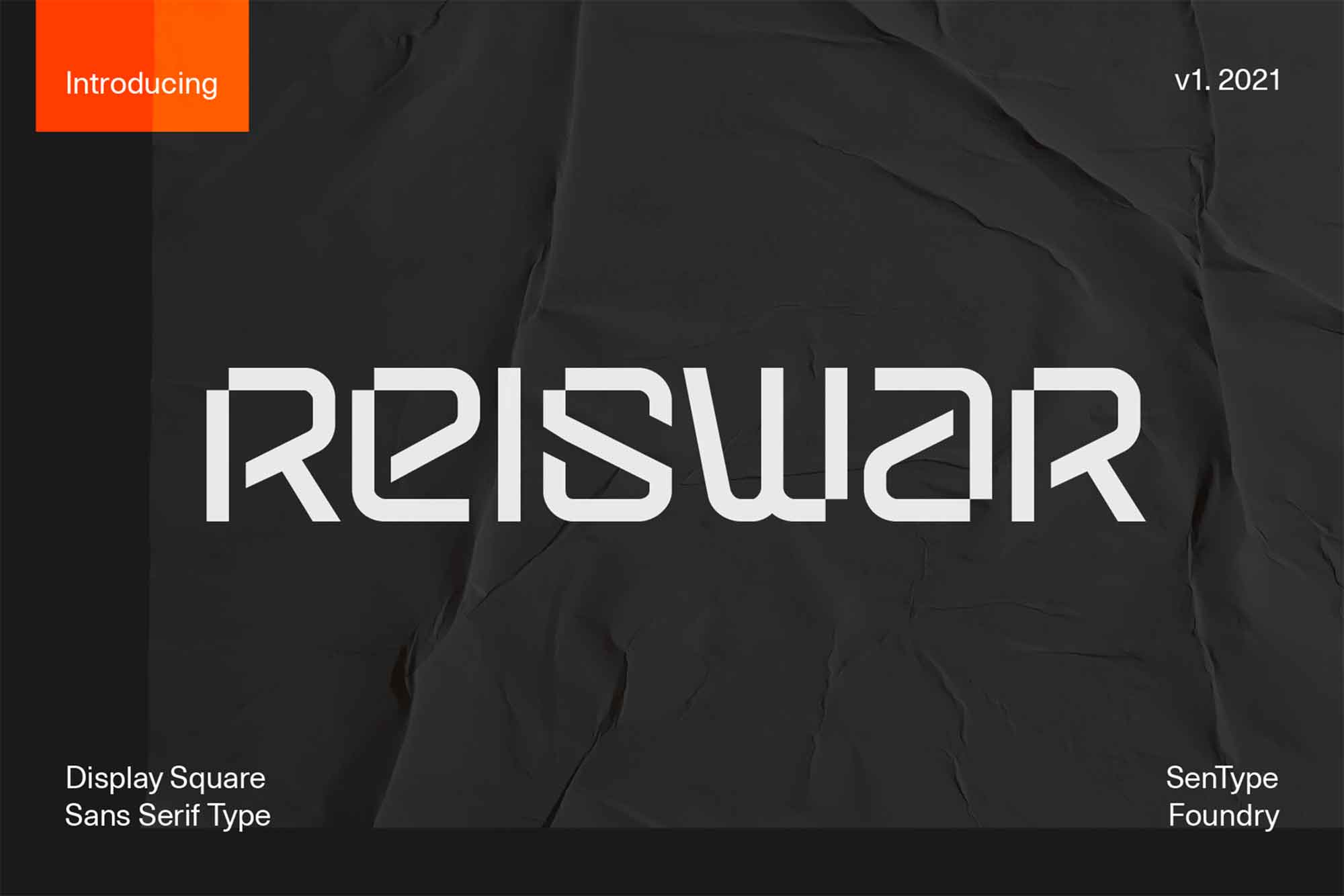
Reiswar é uma fonte de display com uma estrutura geométrica uniforme e estilo monoline. Suas letras têm um toque interessante, especialmente quando os ângulos de letras vazias criam um efeito intrigante. Essa fonte mantém um contraponto elegante entre os caracteres maiúsculos e minúsculos, dentro de um formato quadrado, tudo isso de uma maneira inteligente e única. Perfeito para aplicar em elementos gráficos como títulos e cabeçalhos, Reiswar não apenas destaca seu conteúdo, mas também adiciona um toque de sofisticação ao seu design. Sempre uma opção para quem procura uma fonte de display que se destaca sem perder a essência da legibilidade.